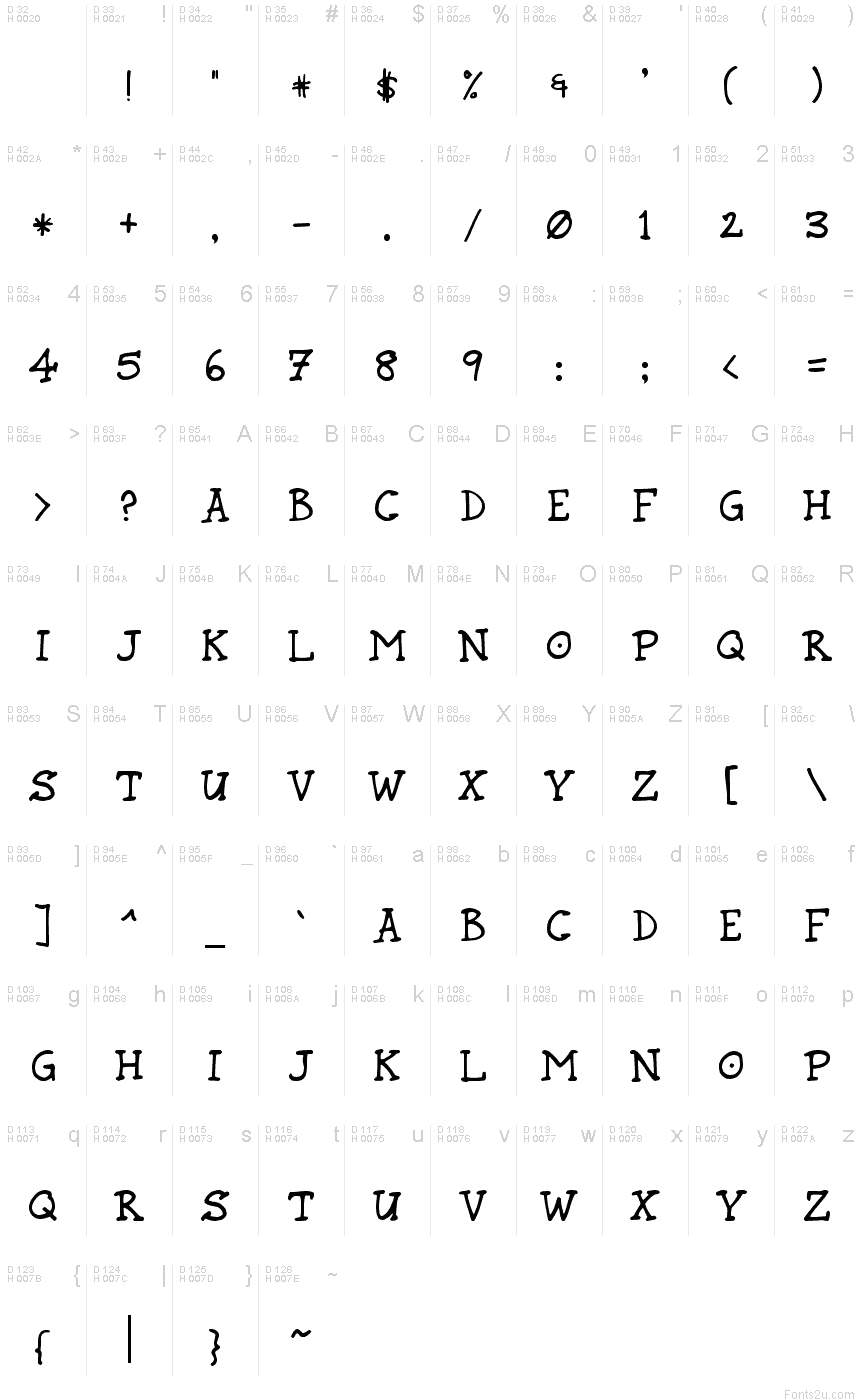
Rund Marker od ZETAfonts je bezplatné ručně kreslené písmo typu marker, které má uvolněný retro nádech jako nápisy malované štětcem. Písmena jsou široká a lehce nepravidelná, se zaoblenými spoji, měkkými zakončeními a ležérním rytmem, díky kterému silné tahy nepůsobí strojeně ani geometricky.
Skvěle funguje na nadpisy plakátů, přebaly alb, branding kaváren, titulky nebo krátké texty na obalech, kde je potřeba, aby písmo působilo hřejivě a ne příliš uhlazeně. Protože tvary působí spíše jako od štětce než jako kaligrafie, hodí se také pro monogramy a velké iniciály, zejména pokud hledáte něco výrazného, přátelského a s trochou syrovosti.